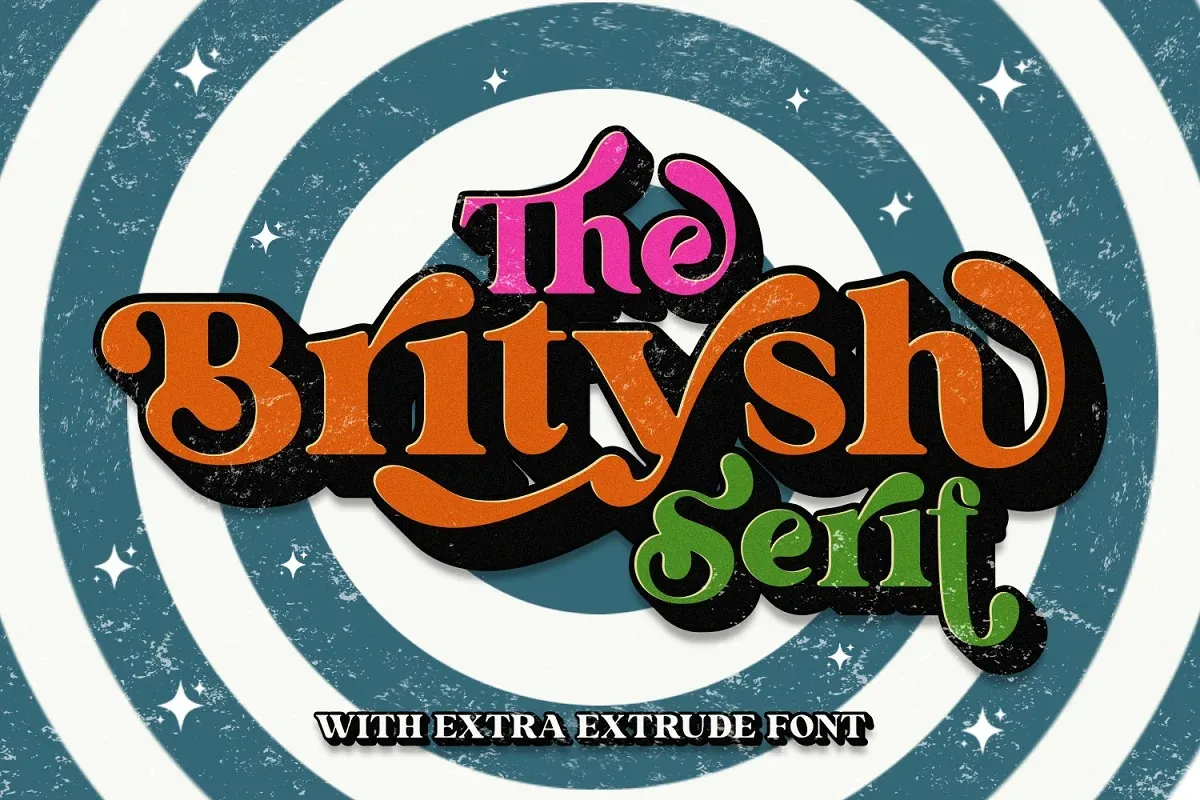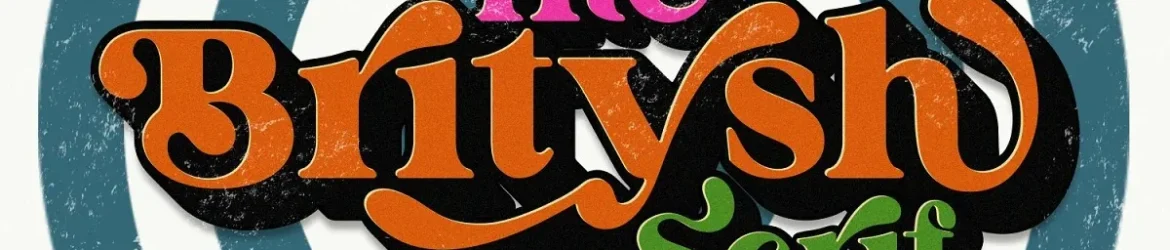
A fonte “Britysh Font” oferece uma experiência visual única que combina elementos modernos com estilos vintage elegantes. Inspirada no designer Sealoung, essa serif é um belo equilíbrio entre a contemporaneidade e o passado retrô. Com sua contraste moderado e características de estilo vintage, esta fonte permite criar designs multifacetados e únicos em poucos segundos, tudo isso com facilidade ao usar stack-in. Perfeita para uma variedade de projetos que exigem clareza visual como logotipos, embalagens de produtos, marca, design de casamentos, anúncios, cartões de convite ou até mesmo assinaturas, a fonte “Britysh Font” é o recurso gráfico ideal para todos os seus projetos visuais.